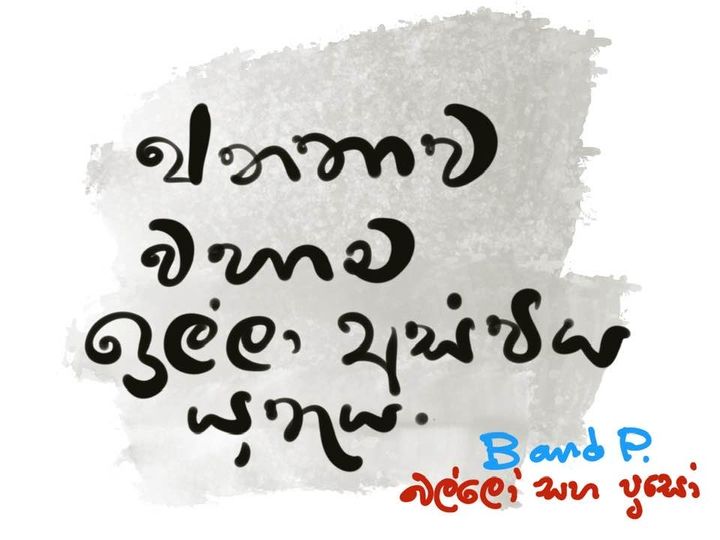
මේ Font එක මොකක්ද.
saradiyel_uk Well-known member May 9, 2010 2,669 3,575 113 Jun 3, 2021 #1 මේ Font එක මොකක්ද. Attachments 188990866_4026308954116806_8388792530095986958_n.jpg 42.3 KB · Views: 133 Reactions: Tharaka_x
dilann Well-known member Jul 6, 2018 68,800 169,265 113 එකමත් එක රටක Jun 3, 2021 #4 font ekk newei.. liyapu ekk Reactions: Tharaka_x
polkichcha Active member Jul 21, 2015 280 89 28 Jun 3, 2021 #5 ලියපු එකක් තමයි "ව " සහ "ය " දෙතැනක දෙවිදිහක් Reactions: BenMacTavish, amino and Tharaka_x
Tharaka_x Well-known member Dec 25, 2017 7,320 9,212 113 26 Matara Jun 3, 2021 #6 dilann said: font ekk newei.. liyapu ekk Click to expand... polkichcha said: ලියපු එකක් තමයි "ව " සහ "ය " දෙතැනක දෙවිදිහක් Click to expand... mamath dakke dan!
amino Well-known member Jul 27, 2008 2,311 2,769 113 Pilimathalawa Jun 3, 2021 #8 polkichcha said: ලියපු එකක් තමයි "ව " සහ "ය " දෙතැනක දෙවිදිහක් Click to expand... rahas parikshakayek api okkoma font eka mokak wenna athida kiyala hithaddi @polkichcha hithala meeka aththatama font ekakda kiyala ela bro
saradiyel_uk Well-known member May 9, 2010 2,669 3,575 113 Jun 3, 2021 #9 නෑ බං FB Post ගොඩක් ෂෙයා උනා ඔය ෆොන්ට් 1ක දාලා
saradiyel_uk Well-known member May 9, 2010 2,669 3,575 113 Jun 3, 2021 #11 Al Baik said: meyka thiyenawada? View attachment 128771 Click to expand... Apex Font set eke balanna